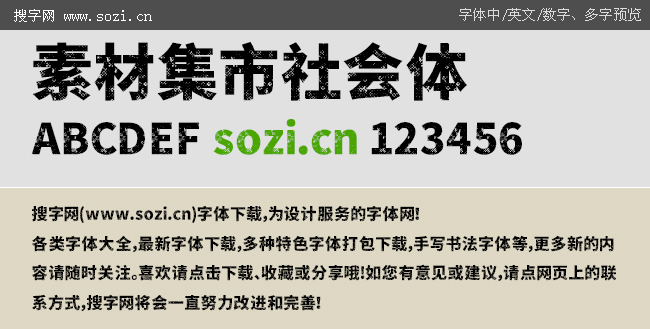
素材集市社會體
搜字網(wǎng)給大家提供一款素材集市社會體中文字體下載,素材集市社會體是一款基于思源黑體-Black字型上創(chuàng)建的字體,在不破壞原有字型的基礎(chǔ)上,添加了破舊斑駁效果,獨特的破舊字型充滿復(fù)古懷舊風(fēng)。適用于海報設(shè)計、網(wǎng)頁設(shè)計、包裝設(shè)計等應(yīng)用。